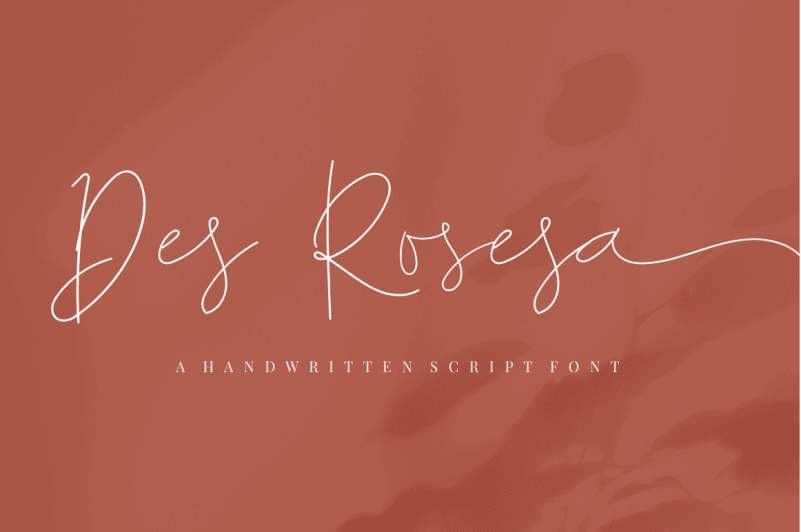
Aqui está uma versão suave e natural do texto para a descrição da página de download da font ‘Des Rosesa Handwritten Font’: Nossa fonte Des Rosesa é perfeita para quem busca um estilo moderno, mas também deseja uma pegada casual e autêntica. Ela foi desenvolvida para ser usada em diversas aplicações, incluindo cabeçalhos de blog, logotipos, roupas personalizadas, cartões de aniversário e até mesmo capas de livros. O que torna a Des Rosesa ainda mais especial é sua capacidade única de combinar o moderno com o natural. Esta fonte foi projetada para manter uma escrita cuidadosamente feita, mantendo um equilíbrio entre aparência elegante e personalização direta, que faz dela uma escolha perfeita para aplicativos variados. Ela é complementada por 101 ligaturas personalizadas, permitindo aos designers criarem combinações de letras atraentes e únicas. Para os amantes do design gráfico, o Des Rosesa é um recurso valioso que pode ser usado em muitos setores da indústria. Além disso, sua versatilidade e facilidade de uso fazem dela uma escolha ótima para designers criativos e aspirantes a freelancers. Com certeza, ela dará seu trabalho um toque único e personalizado que vai destacar seus projetos em qualquer aplicação.